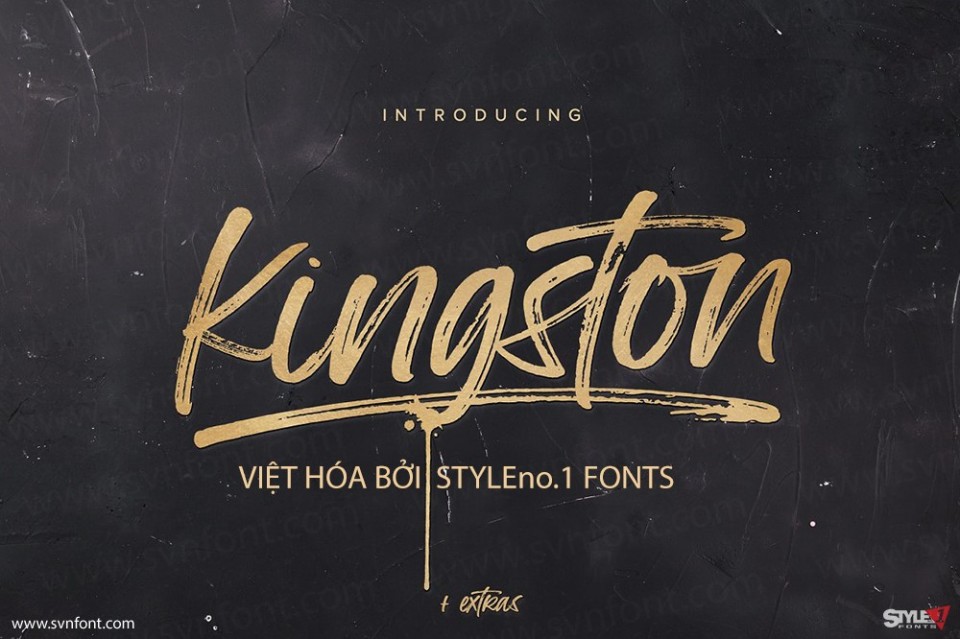
Font việt hóa tiếng việt SVN Kingston
Khám phá sức hút của bộ Font việt hóa tiếng việt SVN Kingston dành cho thiết kế chuyên nghiệp
Giới thiệu về Font việt hóa tiếng việt SVN Kingston
Trong thế giới đồ họa hiện đại, việc tìm kiếm một bộ Font Miễn Phí chất lượng luôn là ưu tiên hàng đầu của các nhà thiết kế. Font việt hóa tiếng việt SVN Kingston nổi lên như một lựa chọn hoàn hảo nhờ sự kết hợp tinh tế giữa nét cổ điển và hơi thở đương đại. Được tinh chỉnh kỹ lưỡng để phù hợp với bảng mã tiếng Việt, bộ font này giúp người dùng xóa bỏ hoàn toàn nỗi lo lỗi font khi gõ các ký tự có dấu phức tạp.
Đặc điểm nổi bật của bộ Font việt hóa tiếng việt SVN Kingston
Thiết kế sang trọng và đa dụng
SVN Kingston sở hữu đường nét dứt khoát nhưng không kém phần mềm mại, tạo nên vẻ ngoài thanh lịch cho mọi ấn phẩm. Đây là mẫu chữ lý tưởng cho các dự án thiết kế bìa sách, poster sự kiện hoặc bộ nhận diện thương hiệu cao cấp. Khả năng hiển thị rõ nét trên cả màn hình kỹ thuật số và bản in giúp Font việt hóa tiếng việt SVN Kingston trở thành công cụ đắc lực cho cộng đồng sáng tạo tại Việt Nam.
Tối ưu hóa trải nghiệm người dùng
Bộ font này không chỉ đẹp về mặt thẩm mỹ mà còn được tối ưu hóa về kỹ thuật. Các khoảng cách giữa các chữ cái (kerning) được căn chỉnh chuẩn xác, giúp đoạn văn bản trở nên dễ đọc và chuyên nghiệp hơn. Đối với các bạn học sinh và giáo viên, việc sử dụng font chữ này trong các bài thuyết trình hay tài liệu giảng dạy sẽ tạo nên sự mới mẻ và thu hút người xem một cách tự nhiên.
Kết luận và trải nghiệm ngay